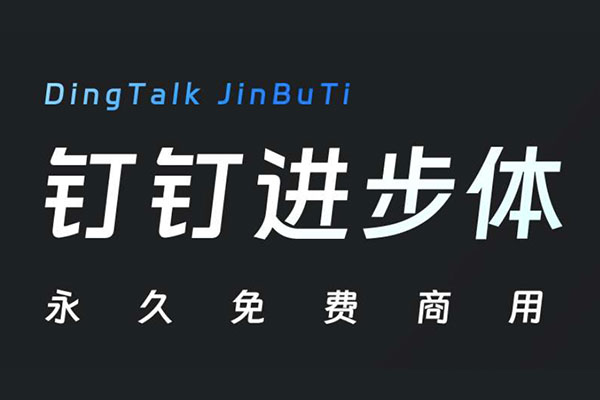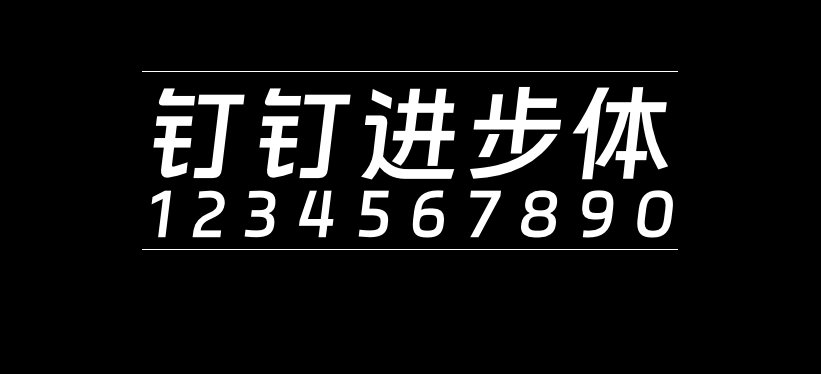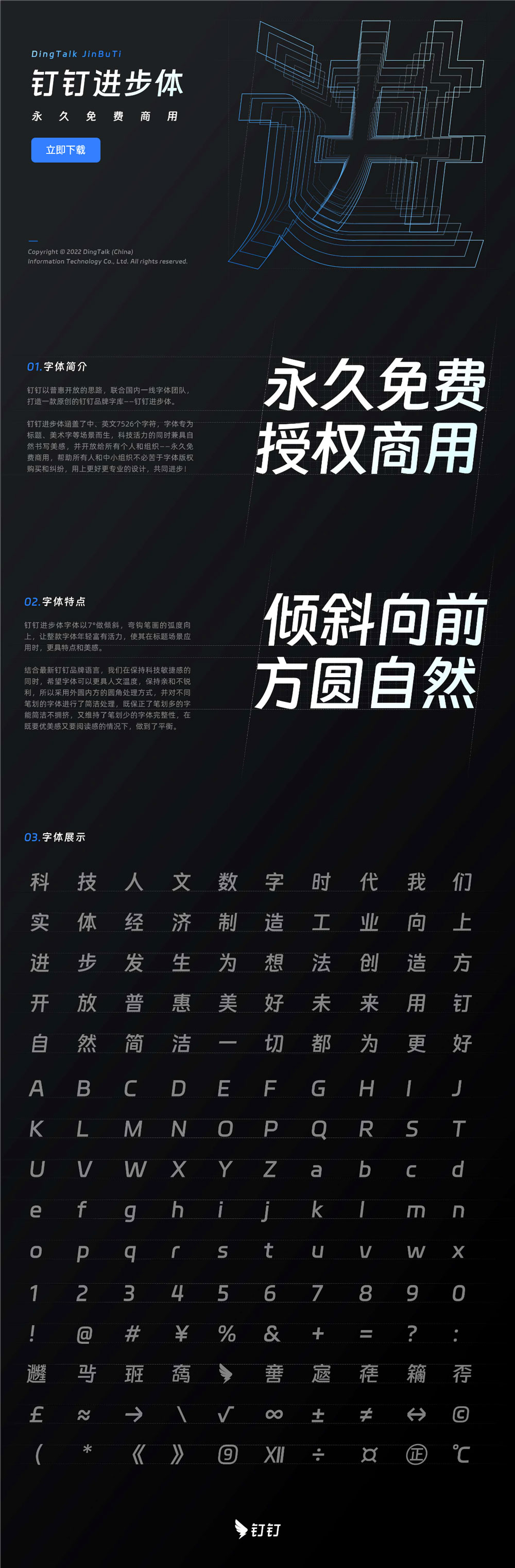
钉钉进步体
钉钉进步体是阿里旗下钉钉产品团队推出的一款简体中文免费商用字体。
简介:钉钉以普惠开放的思路,联合国内一线字体团队,打造一款原创的钉钉品牌字库–钉钉进步体。钉钉进步体涵盖了中、英文7526个字符;字体专为标题、美术字等场景而生,科技活力的同时兼具自然书写美感,并开放给所有个人和组织–永久免费商用,帮助所有人和中小组织不必苦于字体版权购买和纠纷,用上更好更专业的设计,共同进步!
字体特点:
钉钉进步体字体以7°做倾斜,弯钩笔画的弧度向上,让整款字体年轻富有活力,使其在标题场景应用时,更具特点和美感结合最新钉钉品牌语言,我们在保持科技敏捷感的同时,希望字体可以更具人文温度,保持亲和不锐利,所以采用外圆内方的圆角处理方式,并对不同笔划的字体进行了简洁处理,既保正了笔划多的字能简洁不拥挤,又维持了笔划少的字体完整性,在既要优美感又要阅读感的情况下,做到了平衡。